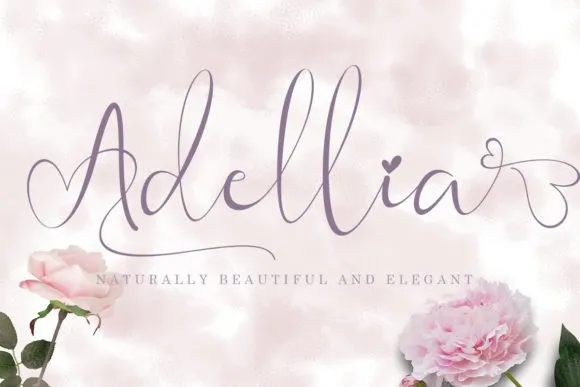
Adellia Calligraphy Font – Download Grátis
A Adellia Calligraphy Font surge no moderno estilo do tipo de letra com uma estreita e perfeita escrita que leva à uma formação arrojada, criada pelo font designer yogaletter6. Este é um tipo de letra de alto nível, encantadora e chega a ser romântica. Ideal para tornar suas trabalhos ainda mais sofisticados e elegantes. Sua perfeita escrita, tanto no início quanto no final, faz dela uma escolha perfeita para qualquer trabalho, seja na criação de cartões de festas, gráficos ou até mesmo em design editorial. Adellia é a fonte que você procura para dar um toque delicado e romântico aos seus trabalhos, tornando seu projeto ainda mais sofisticado e único. Não perca essa oportunidade de revolucionar sua maneira de expressar seus ideais estéticos.